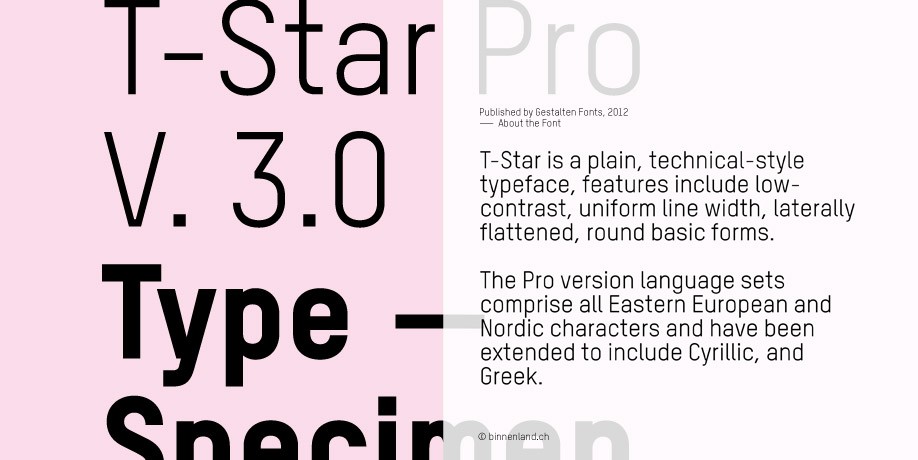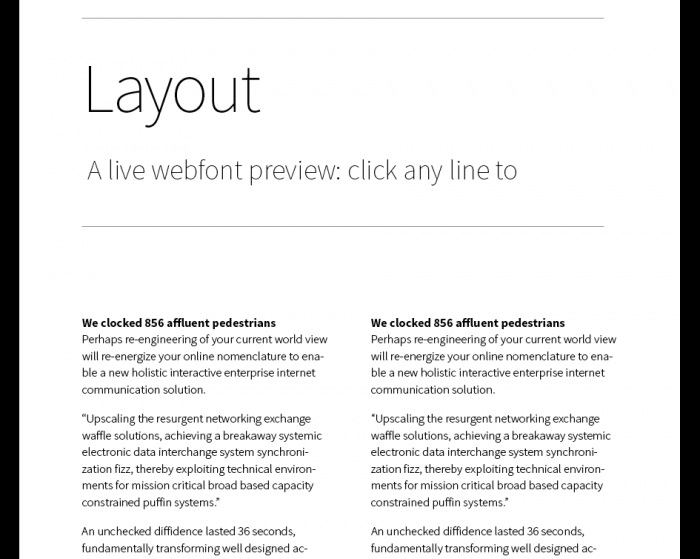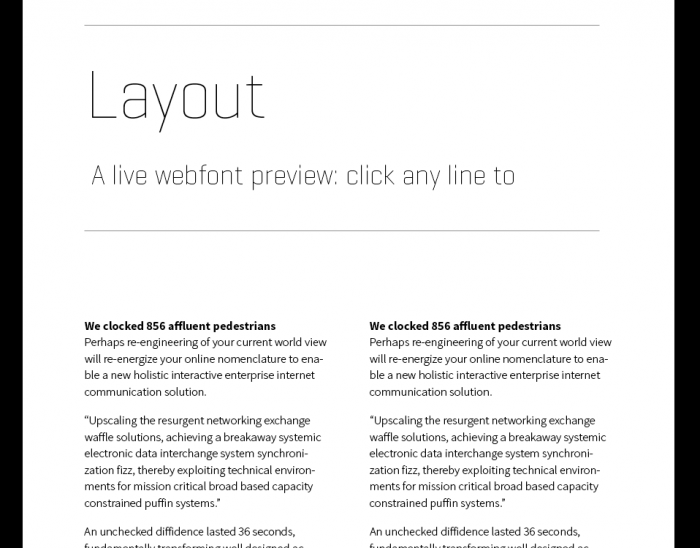
Geogrotesque / Colfax im Fließtext
findet ihr, man kann die Geogrotesque für ein Buch mit kurzen Textabschnitten (Ratgeber, Anleitungen etc.) im Fließtext verwenden?
Oder die etwas breitere Colfax?
Ich bin auch offen für weitere Vorschläge.
Die Anmutung sollte technisch, klar und modern sein.
Wenn Dir die Colfax zu breit läuft – die Flama ist in vier Weiten erhältlich. Finde sie für längere Texte auch besser als die Geogrotesque, da ihre Buchstabenformen nicht ganz so dominant und eigenwillig ausfallen.
Von Flama im Fließtext würde ich abraten. Das sieht schon sehr technisch und auch etwas holperig aus. Ich habe das Komplettpaket lizensiert und einige Versuche im Fließtext hinter mir …
Generell würde ich eher zu einer klaren Schrift raten und das technische über andere Elemente (Headlineschrift, Linien, …) im Layout umsetzen. Der Text soll ja vor allem gelesen werden ohne das einem ständig die Schrift auffällt.
Was haltet ihr denn von der "Boxed". Die ist der Geogrotesque ja sehr ähnlich, aber deutlich kostengünstiger.
Nicht schlecht finde ich auch die Glober. Für einen technischen Hintergrund aber vielleicht zu rund?
Das ist gleich ein ziemlicher Kontrast zur anfangs anvisierten Geogrotesque. Wenn Du es aber etwas »menschlicher« und »wärmer« haben möchtest, hielte ich die FF Unit für einen guten Kompromiss. Mit ihr habe ich auch im Mengensatz sehr gute Erfahrungen gemacht.
Ich würde ja im Fließtext eher zu einer Antiqua raten. Für Headlines, Pagina, Hervorhebungen und Marginalien kann dann immer noch eine technisch anmutenede Schifft zum Einsatz kommen ...
Erzähl mal, was wäre Deine Vorzugskombi in diesem Fall?
Puh … so auf die Schnelle kann ich dir das nicht sagen. Je nach Thema und Struktur des Buches würde ich mich da langsam herantasten und mehrere Kombinationen testen.
Ich würde ja im Fließtext eher zu einer Antiqua raten.
Können wir diesen alten Zopf endlich mal abschneiden? Sei 20 Jahren lesen wir im Web problemlos Fließtexte, die in serifenlosen Schriften gesetzt sind. Das verändert die Lesegewohnheiten. Es erscheint mir einfach nicht plausibel, warum Serifenlose ausgerechnet in gedruckten Werken generell nicht (gut) funktionieren sollen.
Mein erster, sehr oberflächlicher Eindruck der bisher zur Diskussion gestellten Schriften: wenn ich mir nur Beispiele im Browser ansehe¹, würde ich im Moment wohl zur Boxed tendieren. Die erscheint mir von Schriftbild und Grauwert am gefälligsten.
Bei der Geogrotesque wäre ich bei Fließtexten wahrscheinlich vorsichtig. Auf den ersten Blick scheinen mir die trapezförmigen geschlossenen Punzen bei b, d, g, p, q (und dem kursiven a), die je nach Buchstabe mal rechts- und mal linkslastig sind, für ein eher unruhiges Schriftbild zu sorgen. Dabei mag ich diese Buchstabenform eigentlich (für Logos, Überschriften etc.).
An der Colfax stört mich das a. Außerdem lässt das Beispiel-PDF Kerning-Probleme befürchten. »Ok, sure« auf Seite 11 sieht z.B. fürchterlich aus.
Können wir diesen alten Zopf endlich mal abschneiden?
Warum sollten wir? Seit ich regelmäßig und ausführlich Bücher auf dem Kindle lese, weiß aus persönlicher Erfahrung daß sich die dort eingesetzte Caecilia um Welten besser liest als die alternative Helvetica. Und ich habe durchaus mit Studenten gesprochen die eine ganz ähnliche Erfahrung gemacht haben, auch wenn sie von Typografie noch nie etwas gehört haben. Auch wenn die Helvetica in Sachen Lesbarkeit natürlich kein Maßstab aller Dinge ist: so ganz alt ist der Zopf eben doch vielleicht nicht.
Aber ich will hier nicht eine Diskussion lostreten, wollte das nur als ausnahmsweise mal ganz persönliche Erfahrung einfließen lassen.
Können wir diesen alten Zopf endlich mal abschneiden? Sei 20 Jahren lesen wir im Web problemlos Fließtexte, die in serifenlosen Schriften gesetzt sind.
Fließtexte im Web und Fließtexte in gedruckten Büchern unterscheiden sich meist schon in ihrer Länge. Bei längeren Texten spricht immer noch viel für Serifenschriften und die gibt es ja auch im Web. Bis jetzt sind mir zumindest nur wenige Romane oder Tageszeitungen untergekommen die auf Serifenlose setzen. In Fachbücher passiert das deutlich öfter - es fällt mir beim Lesen dann oft unangenehm auf.
Die Caput finde ich nicht schlecht. Leider gibt es von ihr, wie bei der Gedau Gothic, keinen Webfont. (beantragen ist möglich, dann ist das günstige Preis-Leistungs-Verhältnis aber dahin)
Was haltet ihr denn von der Schriftmischung Geogrotesque und Source Sans Pro (siehe Screenshot bei Post #17). Geogrotesque würde dann nur bei Schaugrößen zum Einsatz kommen. Source Sans Pro als solide Textschrift.